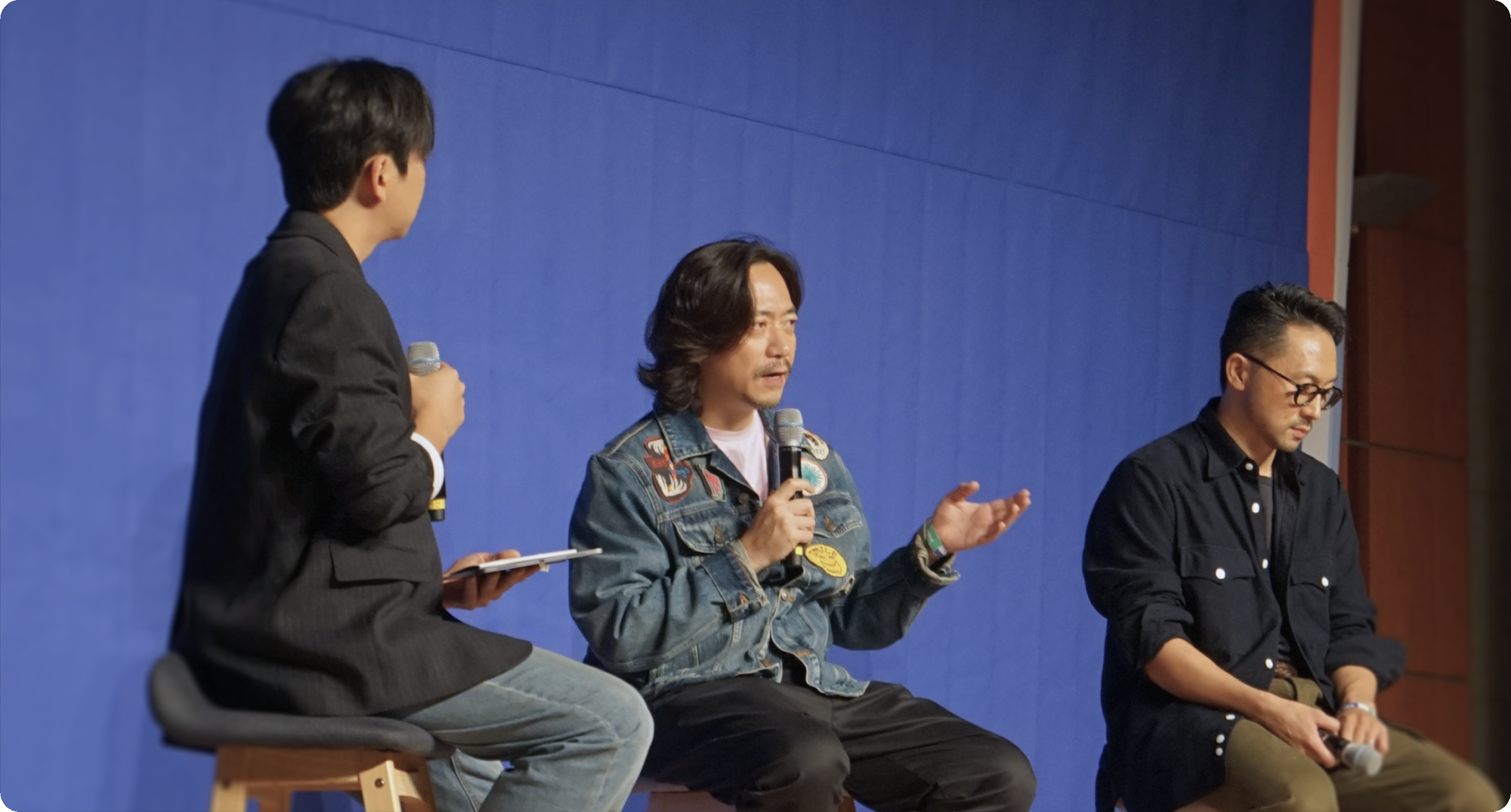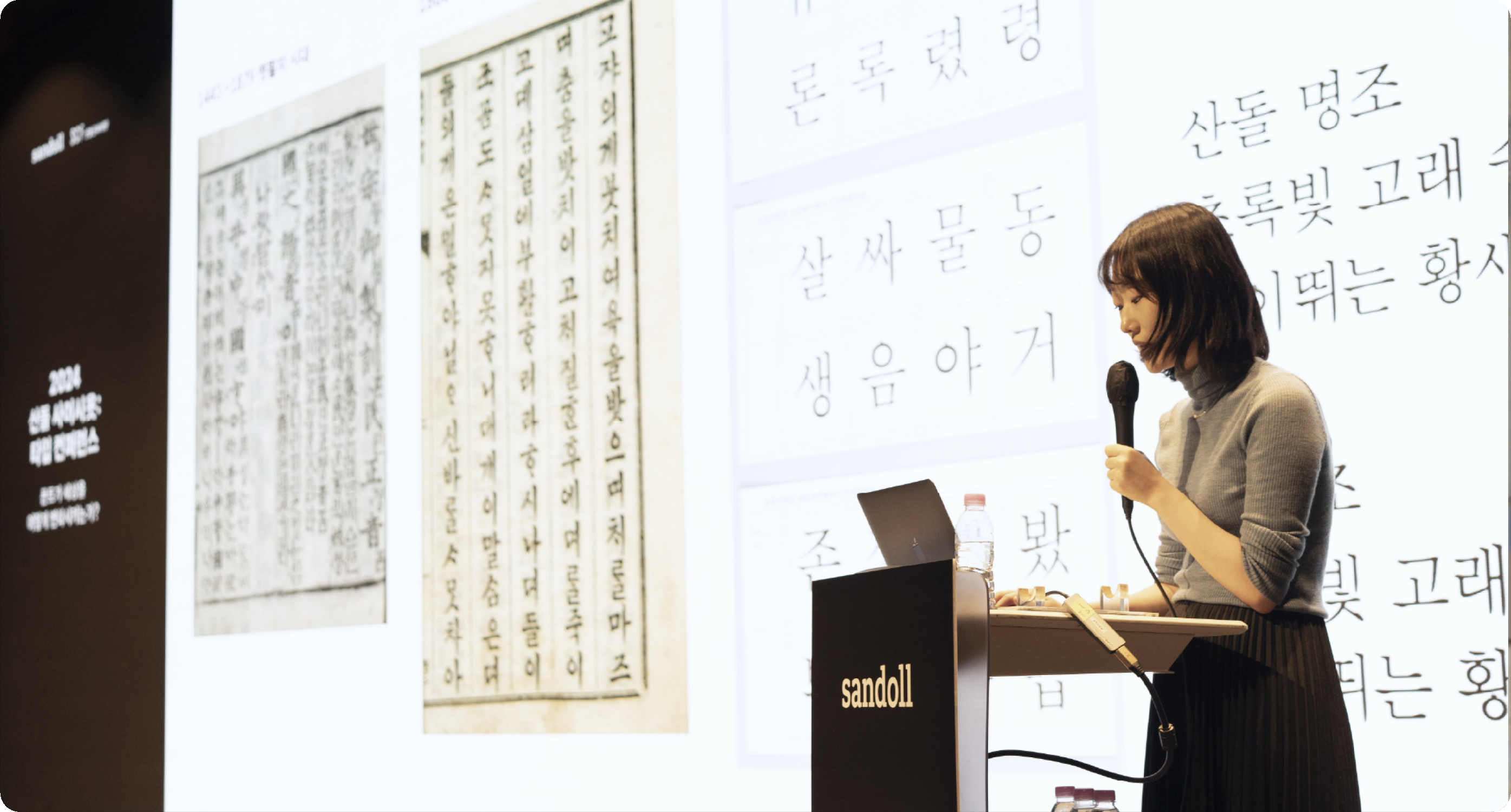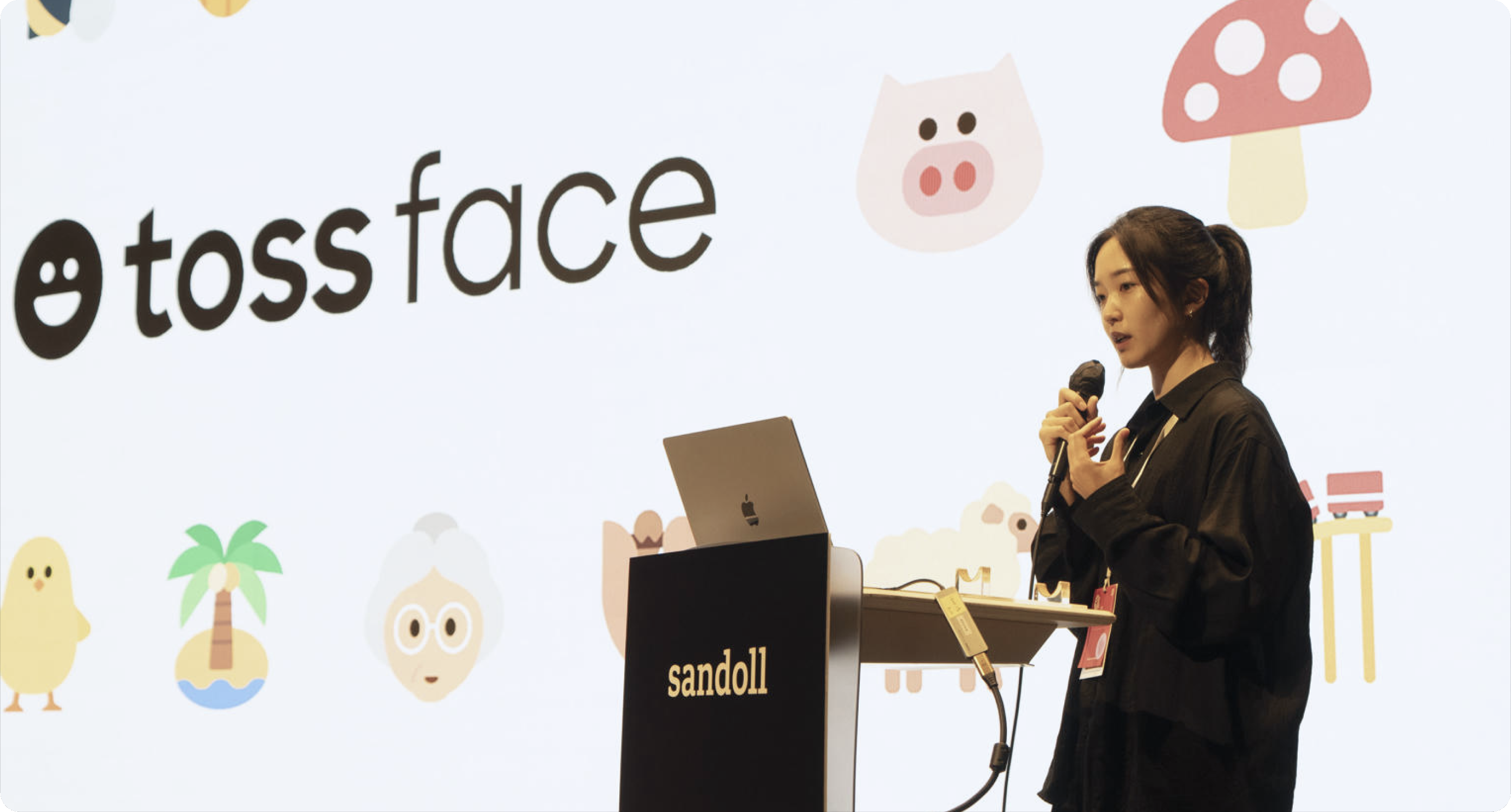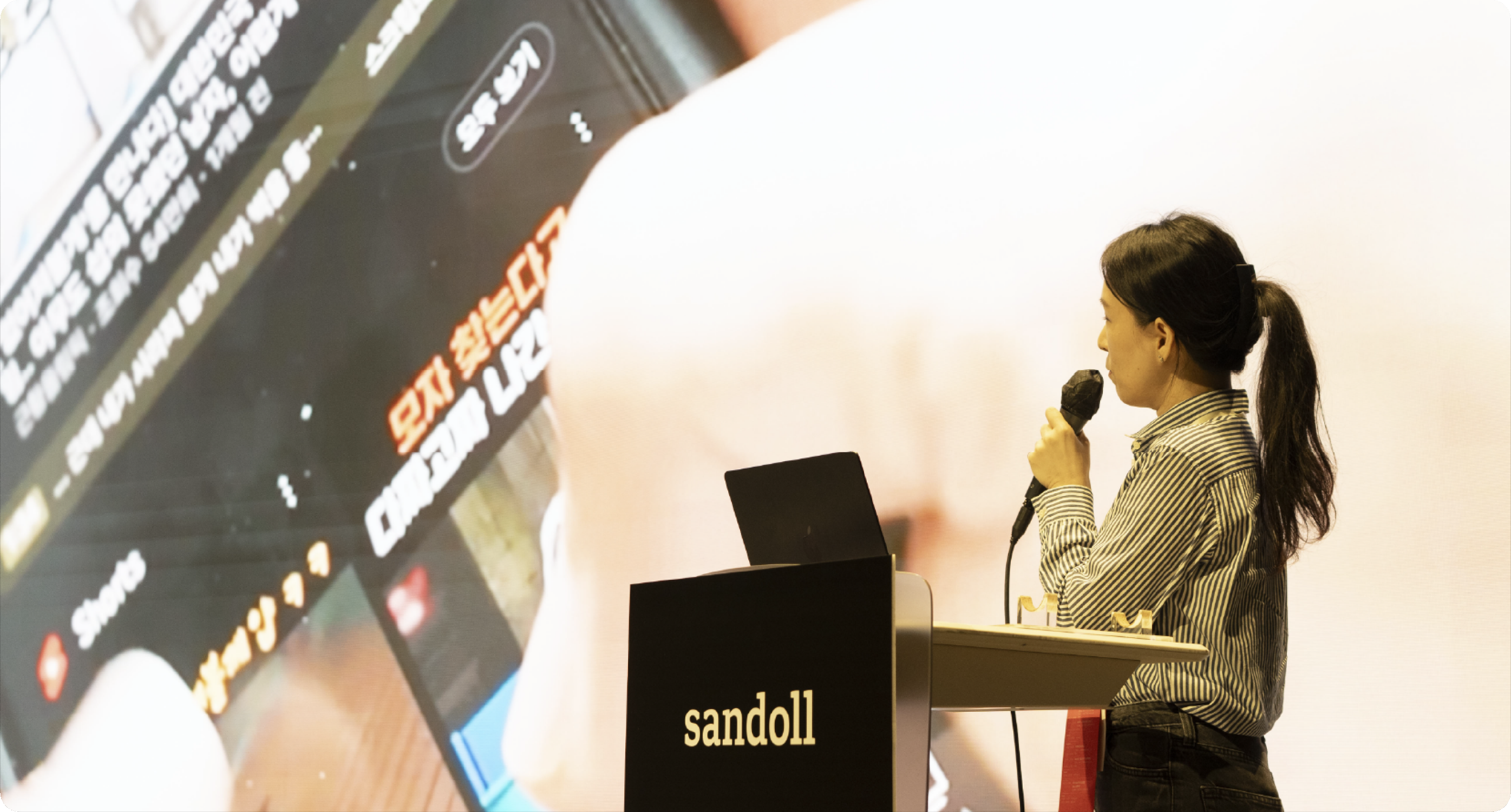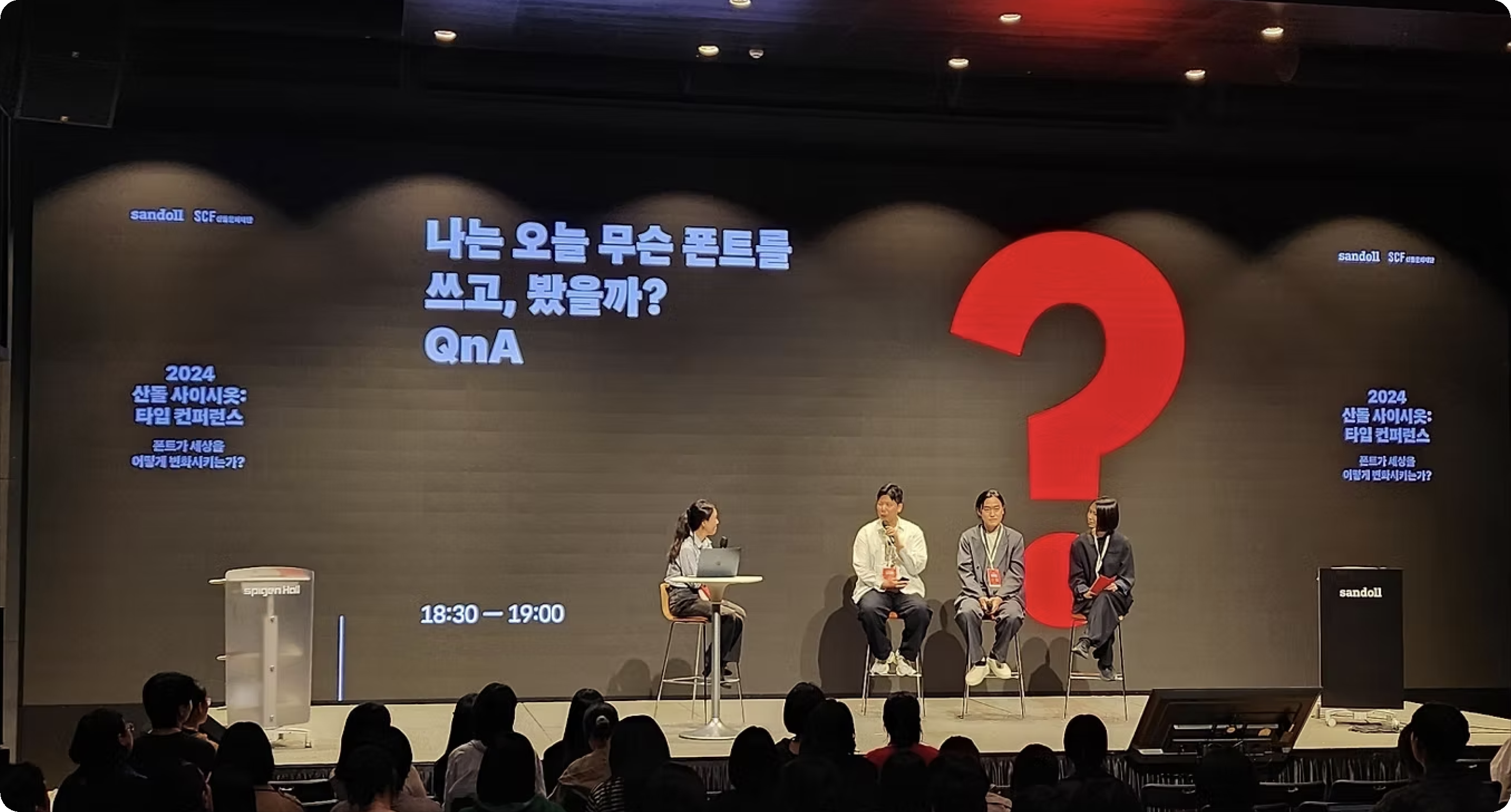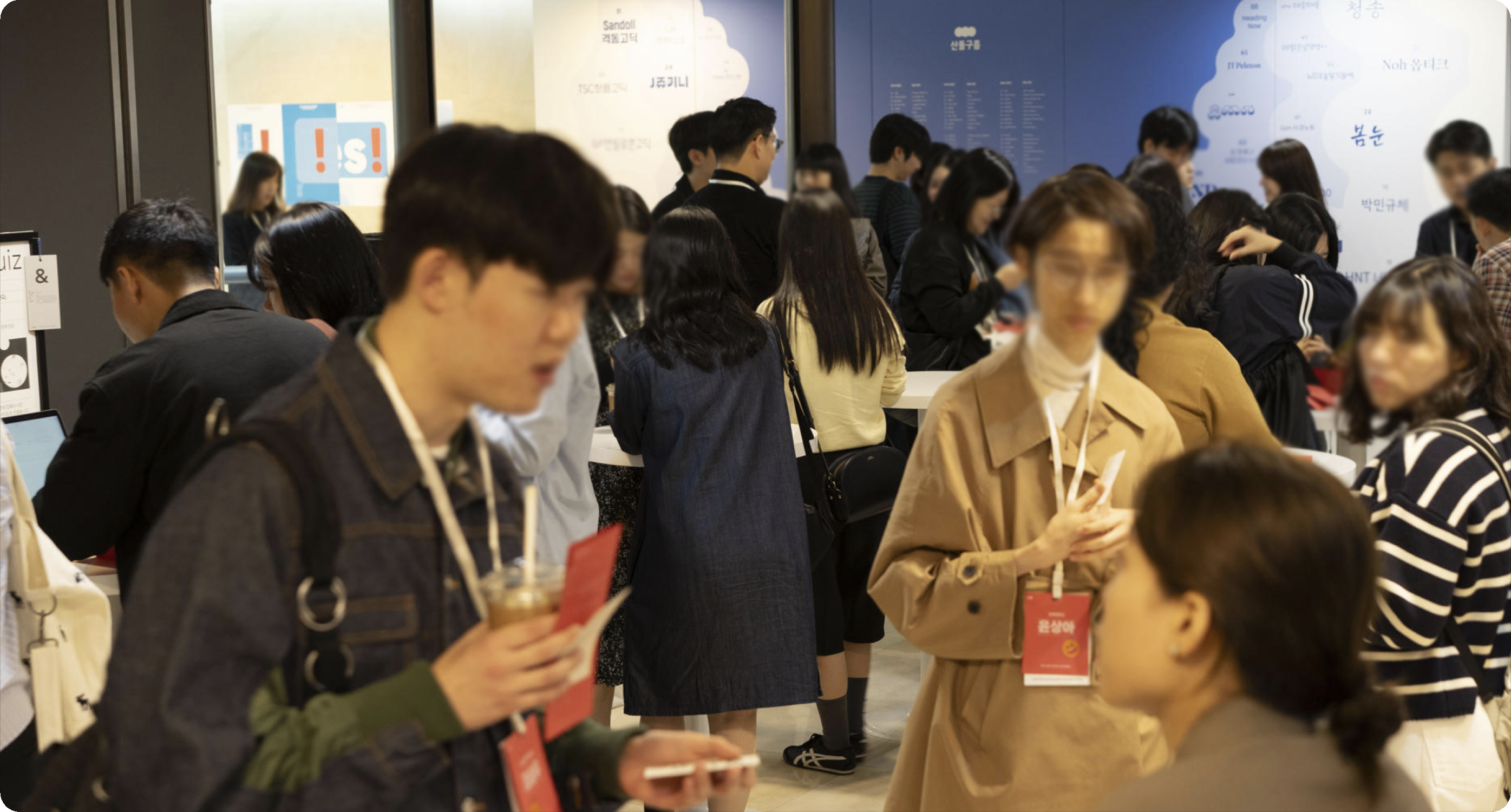
TYPE FOR ALL
모두를 위한 문자
산돌 사이시옷 2026은 다음의 질문을 던집니다.
문자는 누구를 위해 설계되는가.
읽기와 쓰기의 장벽은 어떻게 낮아질 수 있는가.
글로벌 환경에서 문자는 어떻게 공존하는가.
더 많은 사람을 위한 Type(글자)와
Type(유형)에 대해 이야기합니다.
Speaker & Program
국내외 연사들과 함께하는
타입과 디자인 이야기
• 10:40 — 11:10 30분
Type Design Evolution
프리텐다드, 그 다음
길형진 오리온캑터스 디렉터
길형진
• 11:10 — 11:40 30분
Typography Branding
배민 폰트 새롭게 만든 이야기 :
왜 그렇게 했어요?
한명수 우아한형제들 CCO
Anuthin Wongsunkakon
• 13:30 — 14:00 30분
Type Design Type Culture
문자 이면의 문자:
지역의 실천을 넘어 세계와 연결되는
태국 타이포그래피
Anuthin Wongsunkakon Cadson Demak 공동창립자
한명수
• 14:00 — 14:30 30분
Type Design Calligraphy
캘리그라피 원리로 바라보는
다국어 타입디자인
Gia TRAN Babelfont 공동창립자, 폰트 디자이너
Gia TRAN
• 15:30 — 16:00 30분
Graphic Design Solidarity
조화를 만드는 일
이재영 6699press 그래픽 디자이너
이재영
• 16:00 — 16:30 30분
Type Design Universal Design
우리가 모르는 특정한 몸을 위한
글자 디자인
유지원 글문화연구소 연구소장, 작가
유지원
• 10:10 — 11:40 30분
Type Design Lettering
감각을 획으로, 생각을 글자로
채희준 CH Font 대표
채희준
• 11:10 — 11:40 30분
Lettering Experimental
꽤나 이상한 글자
김현진 POT 대표
김현진
• 13:30 — 14:00 30분
Graphic Design Community
주변으로부터:
가까이에서 수신하고 먼곳으로 발신하기
박수연, 장영웅 노네임프레스 그래픽 디자이너
박수연, 장영웅
• 14:00 — 14:30 30분
Type Design Public Design
로컬이 글자로 하고 싶은 이야기
이정은 윤디자인 타입디자인팀장
이정은
• 15:10 — 15:40 30분
Graphic Design Solidarity
시간대와 시차, 그리고 폰트:
프로덕션타입의 파리–상하이 운영 방식
Jean-Baptiste Levée Production Type 창립자, 크리에이티브 디렉터
Jean-Baptiste Levée
• 16:20 — 16:50 30분
Type Design Universal Design
매체 확장과 타이포그래피 실험
신해옥, 신동혁 신신 그래픽 디자이너
신해옥, 신동혁
• 16:50 — 17:20 30분
Graphic Design Language
언어와 디자인 사이에서,
우리가 하는 일
신소현 오이뮤 대표
신소현
Beyond Stage
강연을 넘어, 사람과 경험이 연결되는
산돌 사이시옷만의 특별한 프로그램을 만나보세요
• SAISIOT INSIGHT
강연 중 만난 인상 깊은 문장과 생각을 기록하고,
서로의 인사이트 공유를 통해 참가자와 연사의
네트워킹을 만들어가는 사이시옷 연계 프로그램.
• Networking
연사 및 동료 디자이너들과
직접 마주하며 시선을 나누는 교류의 장
• BRAND EXPERIENCE
타이포그래피의 확장을 오감으로
경험할 수 있는 다채로운 체험 부스
SAISIOT TRIP
SEOUL TYPO SAFARI
서울 타이포 사파리
폰트, 레터링, 그래픽, 일러스트 등 각 분야의
전문 디자이너와 함께
서울 도심을 걷습니다.
서울이라는 도시가 문자를 품어온 방식을 탐구하며,
전문가의 시선으로 걷고 해석
하여
기록한 결과물은 향후 온·오프라인 전시로 이어집니다.